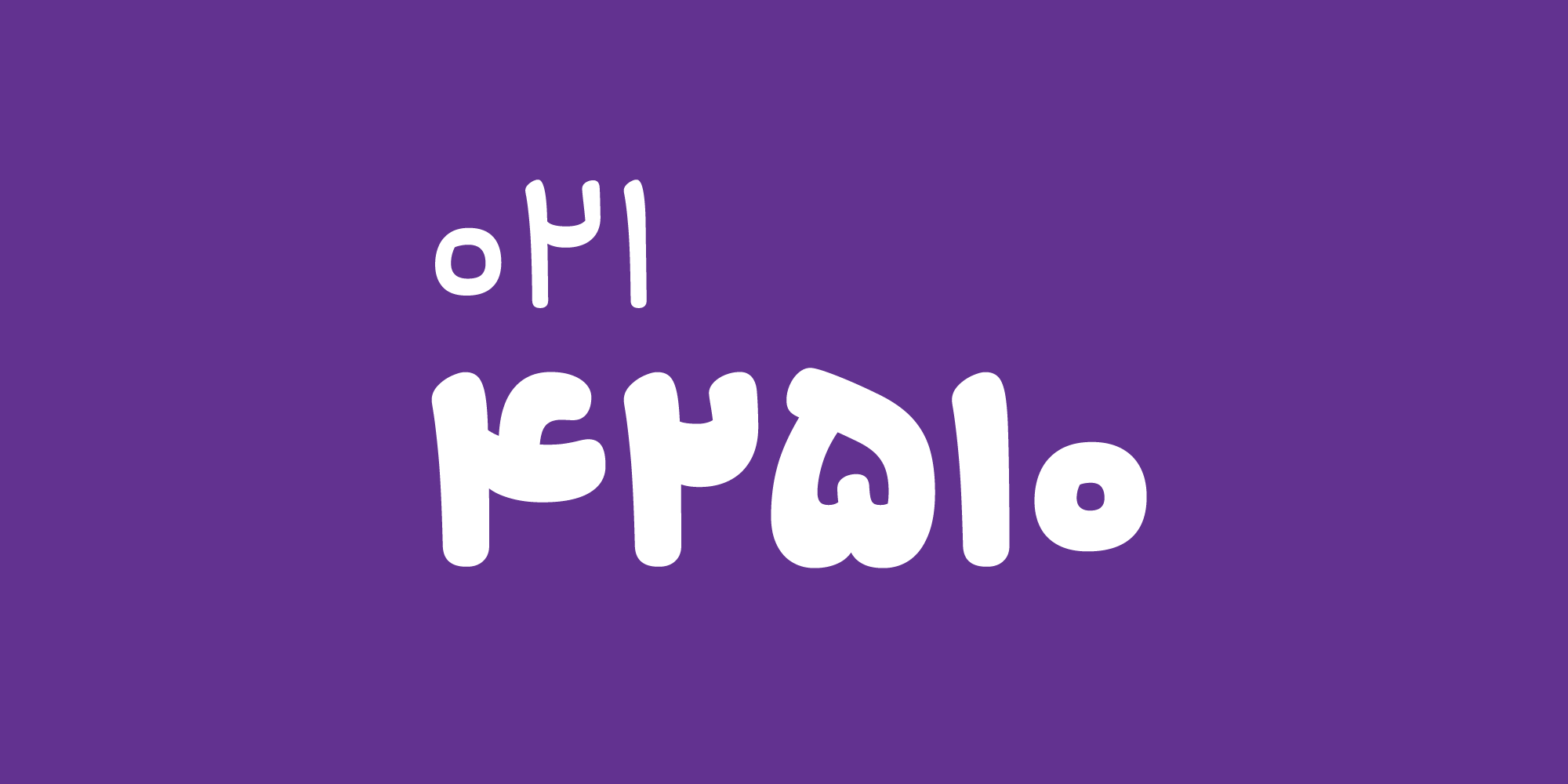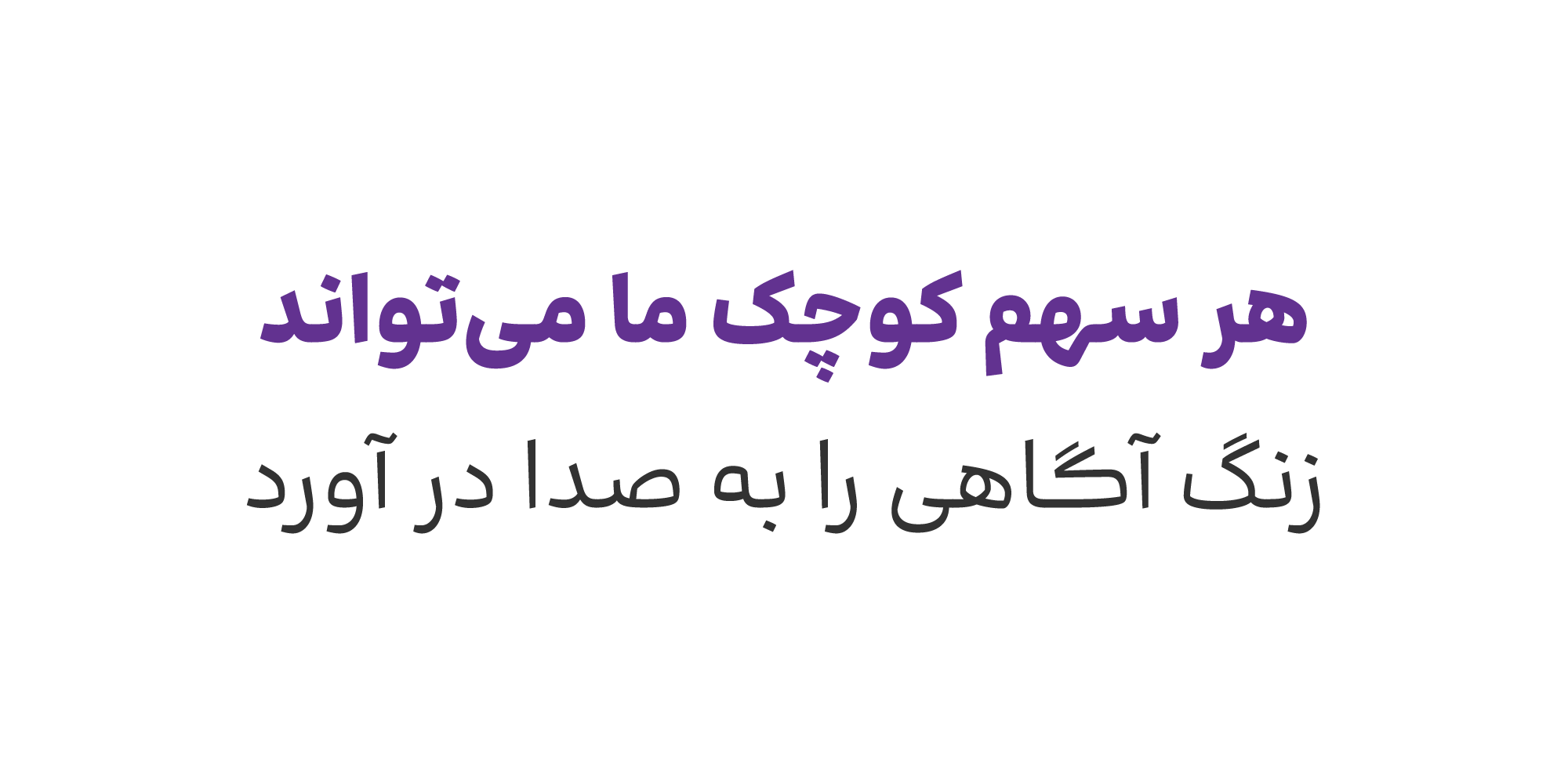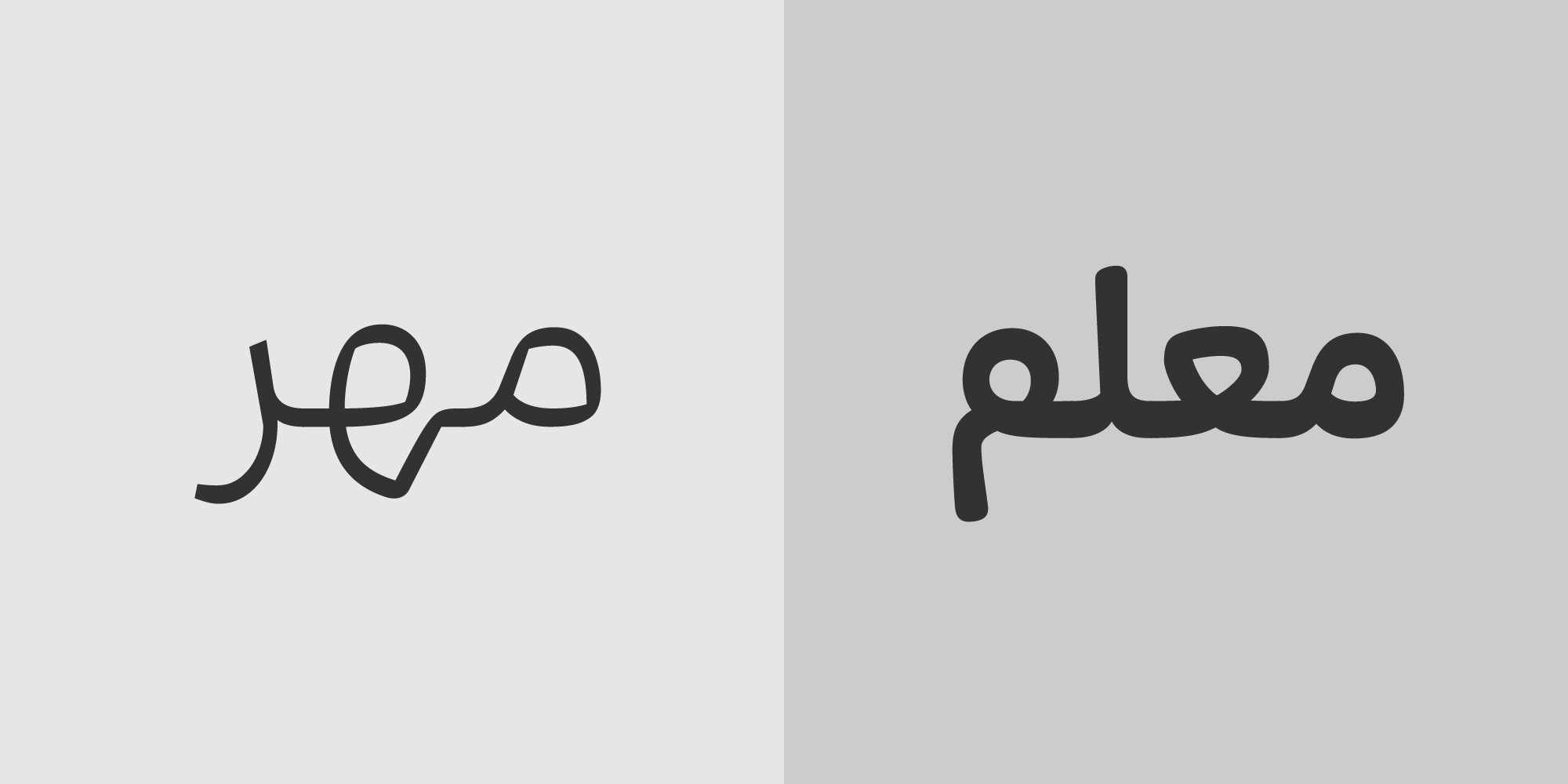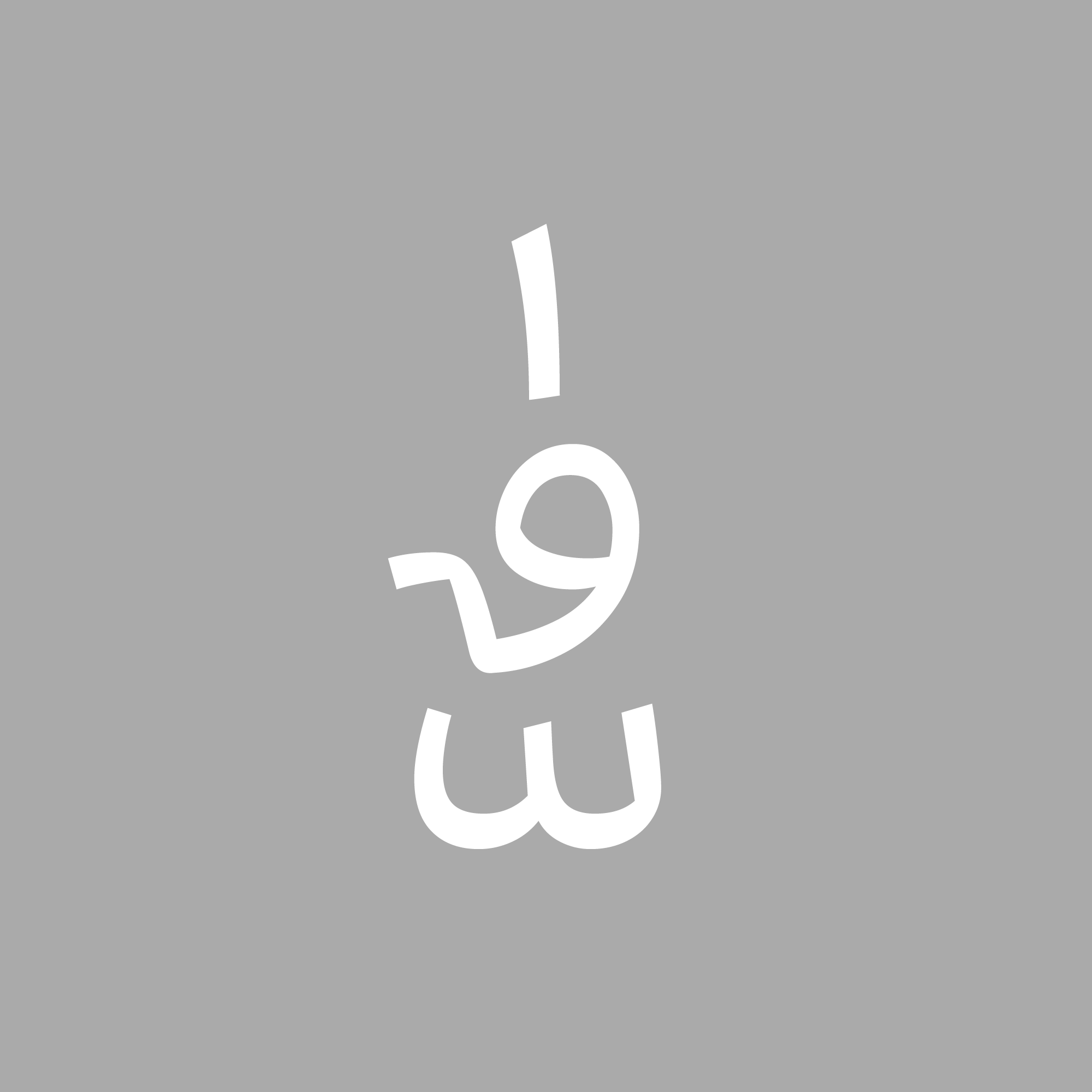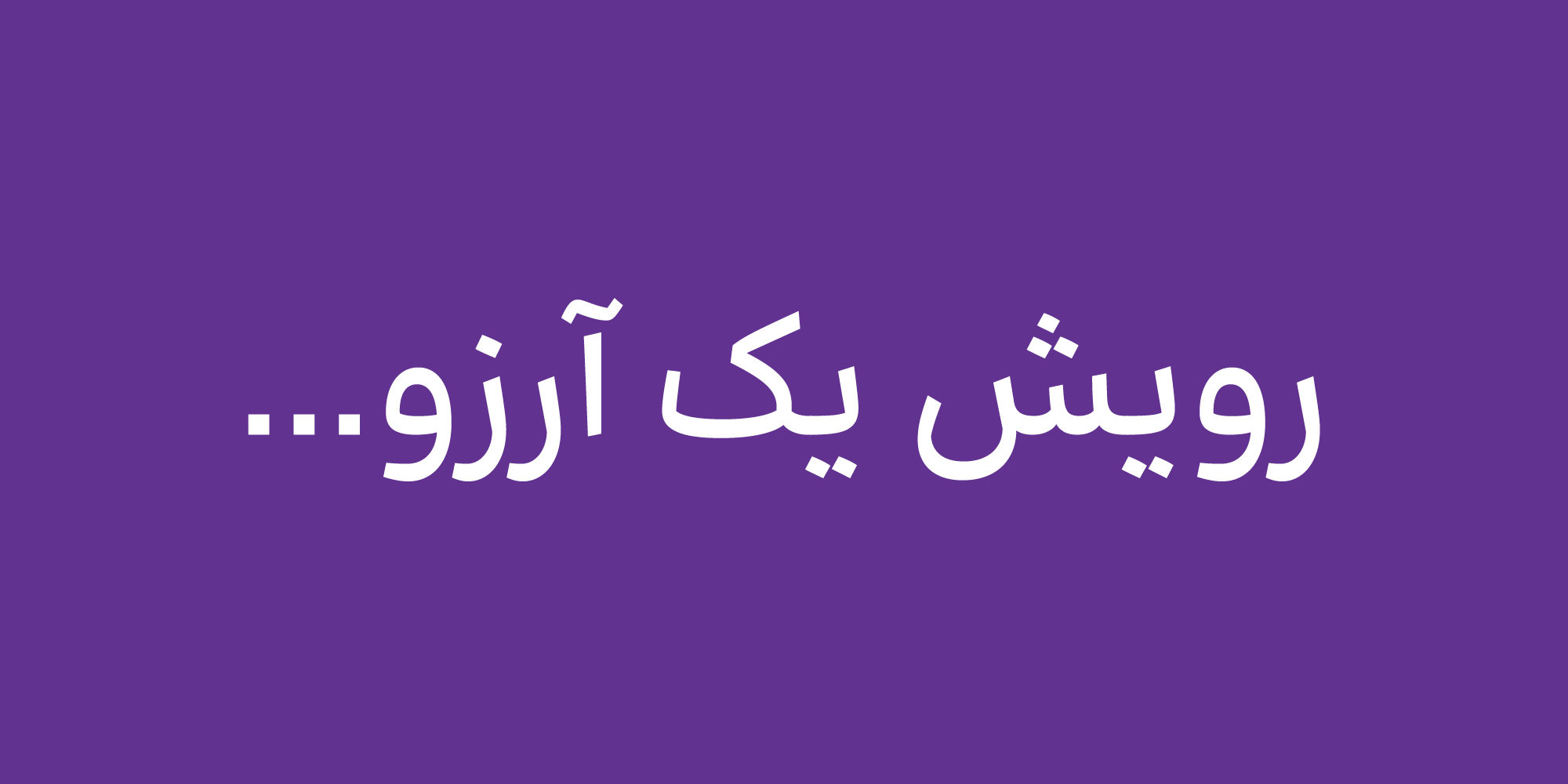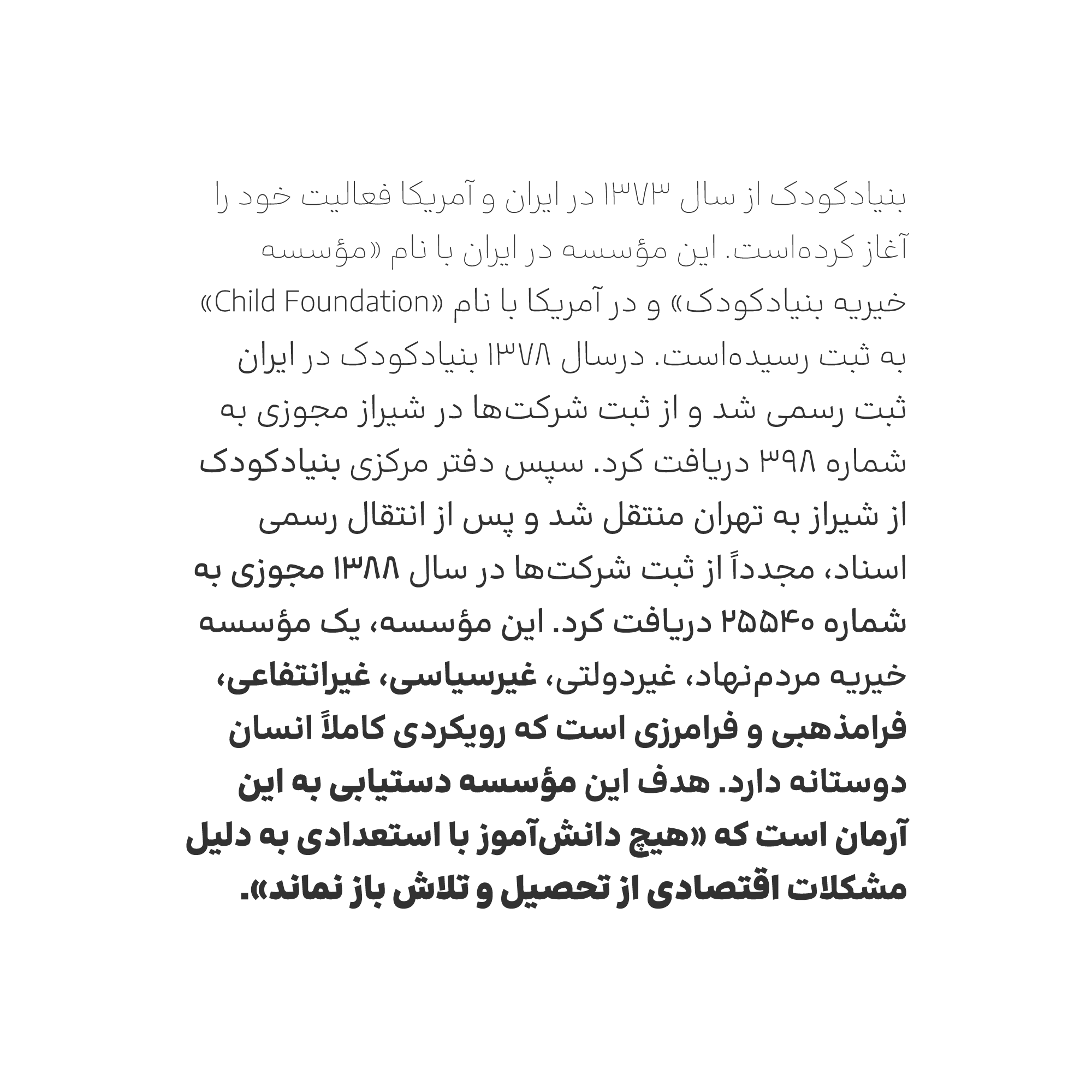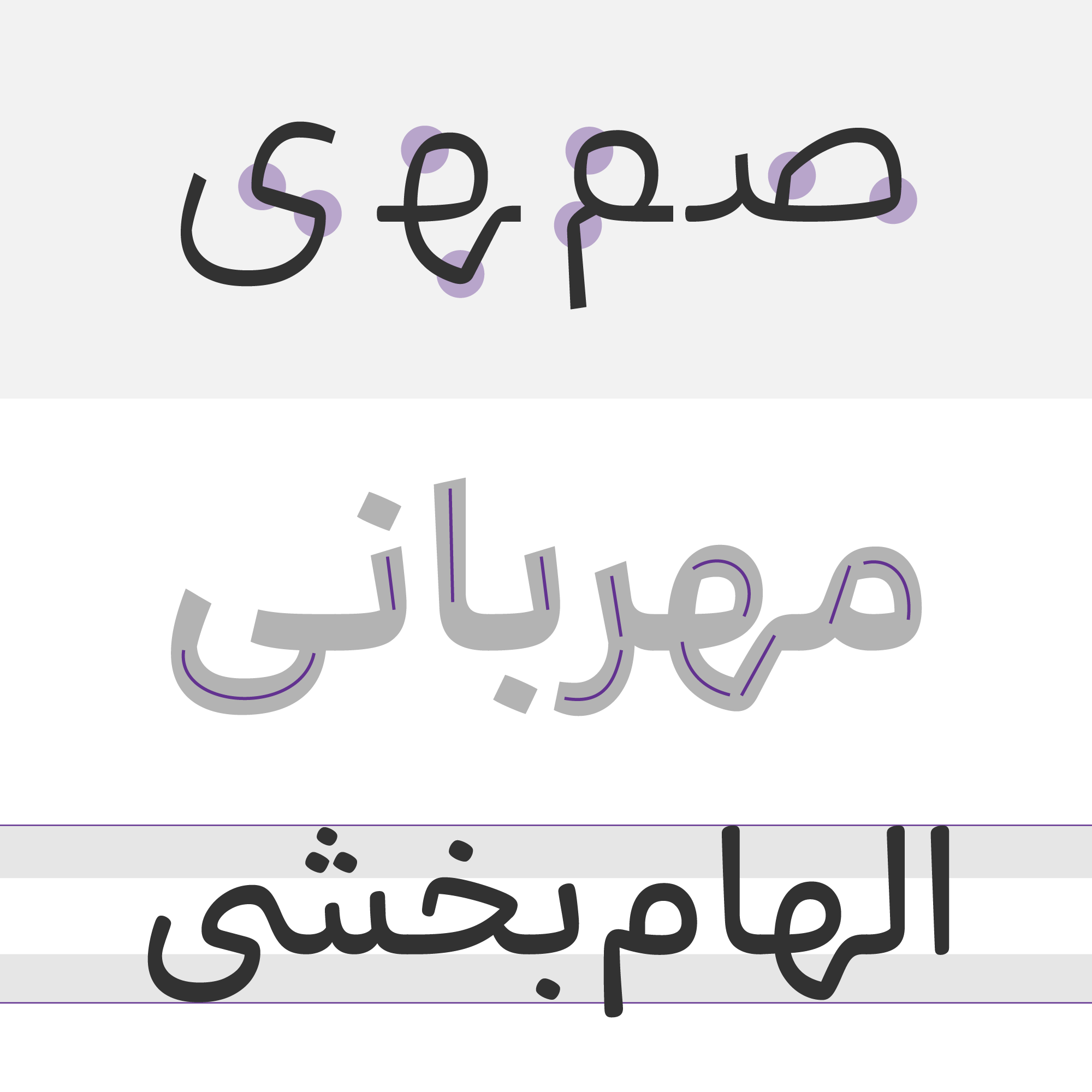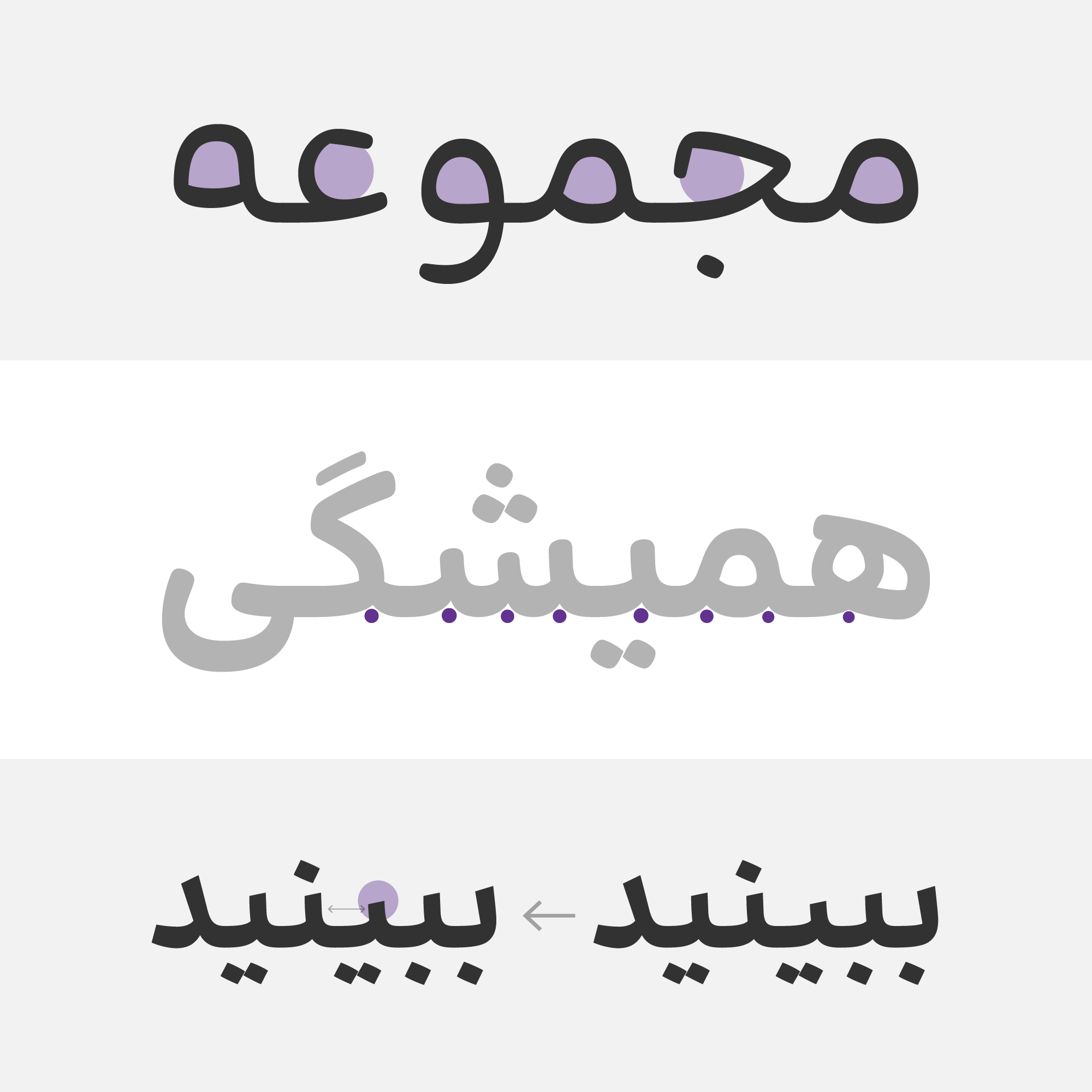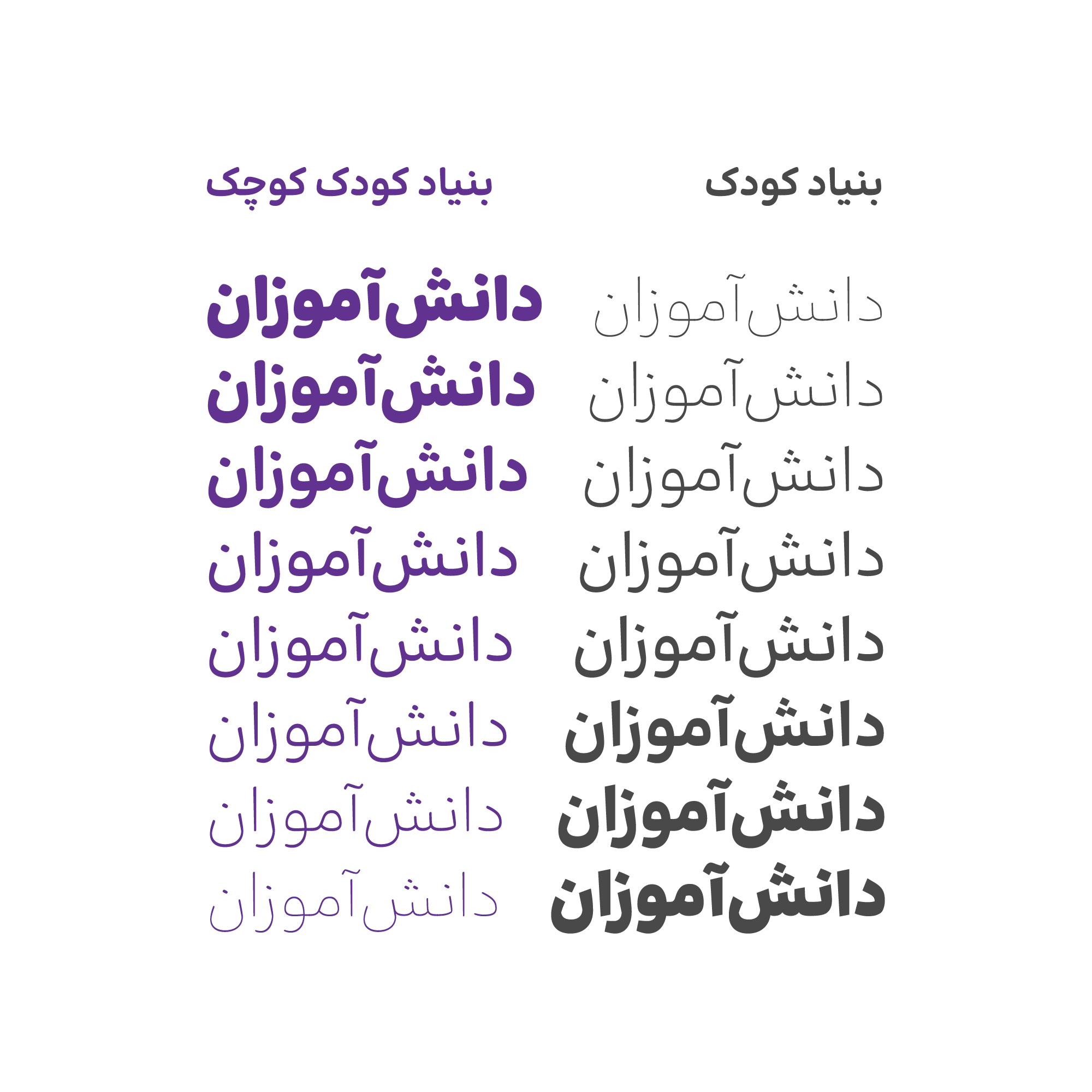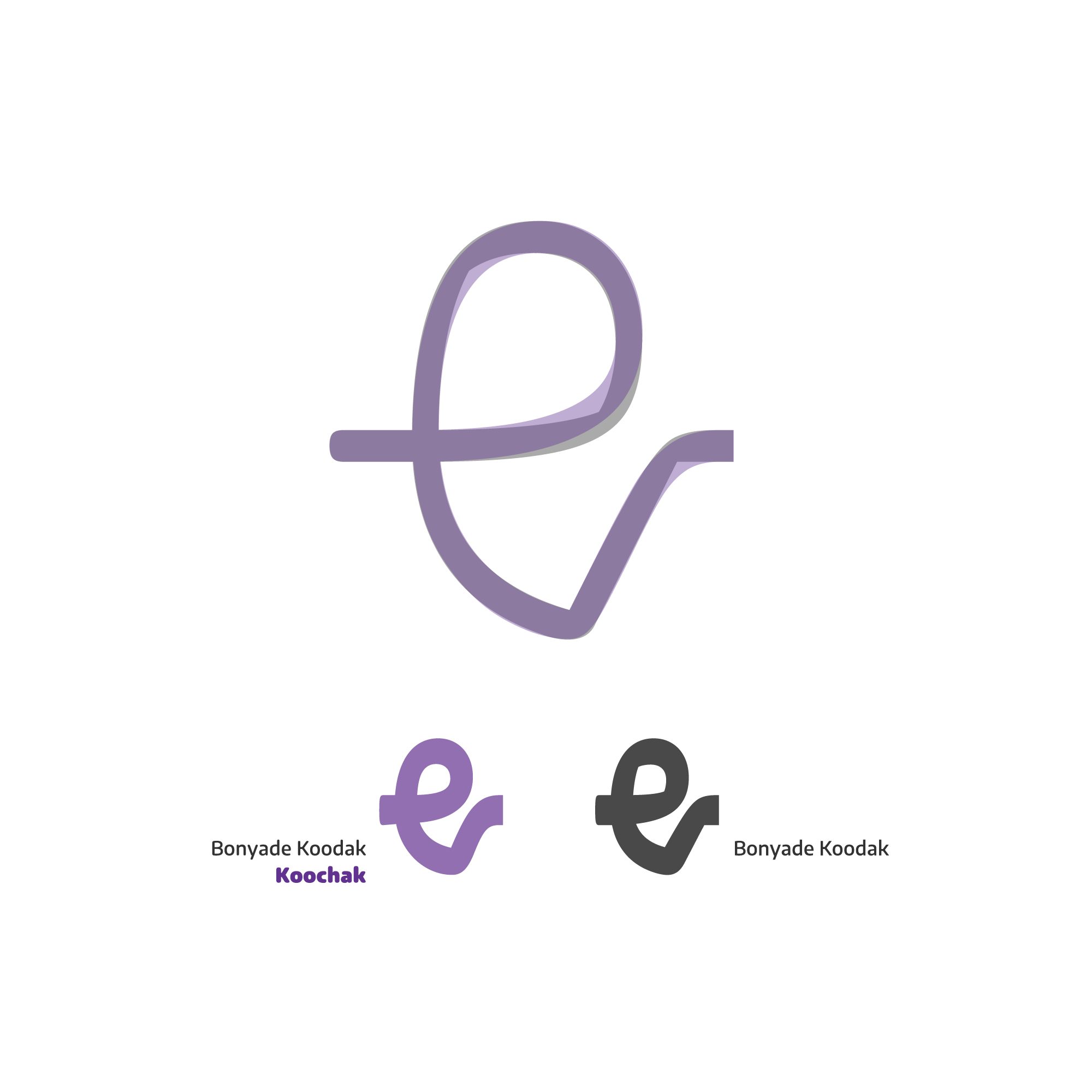
«بنیادکودک» نام مؤسسهای مردمنهاد است که با کمک نیکوکاران در تأمین نیازهای تحصیلی دانشآموزان کمبرخوردار تلاش میکند. این مؤسسه در خلال برنامهریزی برای ریبرندینگ، بهمنظور ارتباطات موثرتر، در اندیشه خلق فونت اختصاصی بود. به این ترتیب تیم طراحی در راستای مسئولیت اجتماعی و با تکیه بر تخصص خود با افتخار با این جریان همراه شد.
با بررسی دادهها و اطلاعات ارائه شده از سوی بنیادکودک و ایدهپردازی بر اساس ویژگیهای اصلی و صفات بارز برند، کار شخصیتبخشی و طراحی کاراکترهای فونت را پیش بردیم. ضمن توجه به «کودکان» که دلیل وجود بنیادکودکاند، «بزرگسال و نیکوکاران» بهعنوان مخاطبان اصلی و «جایگاه و لحن برند» به تعریف شخصیت متناسبی رسیدیم تا جوابگوی نیاز برند باشد. بهطور مثال میزان نرمی حروف را بهگونهای در نظر گرفتیم تا نسبتی با نام بنیادکودک داشته باشد و در عین حال بتواند در نظر مخاطبان پذیرفته شود. فرآیند دیزاین تا اجرای این فونت بهطور کامل در نرمافزار انجام شد.
اکنون بنیادکودک در راستای تأمین نیازهای دانشآموزان تصمیم گرفته فونت اختصاصی خود را به صورت عمومی منتشر کند. تیم طراحی نیز با این تصمیم همراه شد و سبک «کوچک» را طراحی کرد و به مجموعه افزود تا خانوادهی فونت برای عرضهی عمومی جامعتر و کاربردیتر باشد و بتواند نیازهای بیشتری را پوشش دهد.
بنیادکودکِ «کوچک» با بدنهی نرمتر، شکستگیهای کمتر و لبههای گرد، نسخهی کودکانهی فونت است.
فونت بنیادکودک توسط مهدی ارشادی و رضا بختیاریفرد در سال ۱۴۰۱ طراحی شده است. این فونت دارای ۸ وزن، ۲ سبک و نسخهی وریبل است.